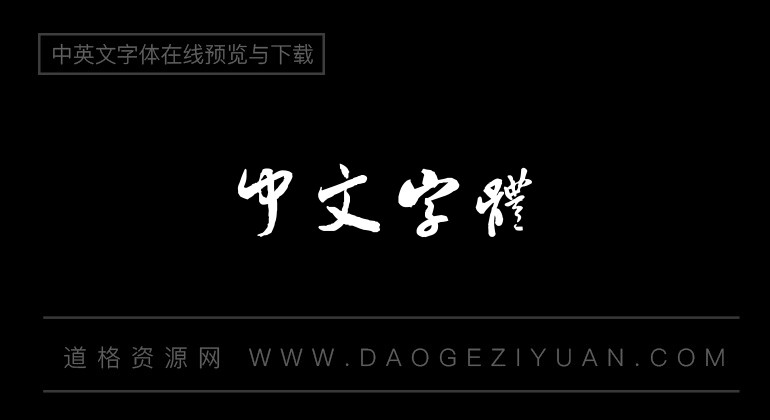
方圆米芾真迹字体是由中国著名设计师米芾设计的一款中文字体,它以汉字传统的繁体形式设计,并以折叠的线条结构表现出汉字的精髓,从而营造出一种独特的视觉效果。字体的特点是极具层次感,外形精细,笔画流畅,笔画之间的距离也很合理,使字体看起来更加立体,更加美观大方。文件名:FangYuanMiZhenJi-JianTi-1.ttf
方圆米芾真迹是一款非常不错的手写艺术字体,具有很好的视觉感,适合于文化类的宣传设计、商业类品牌的广告和产品包装设计以及个性化文字排版等较多场景。